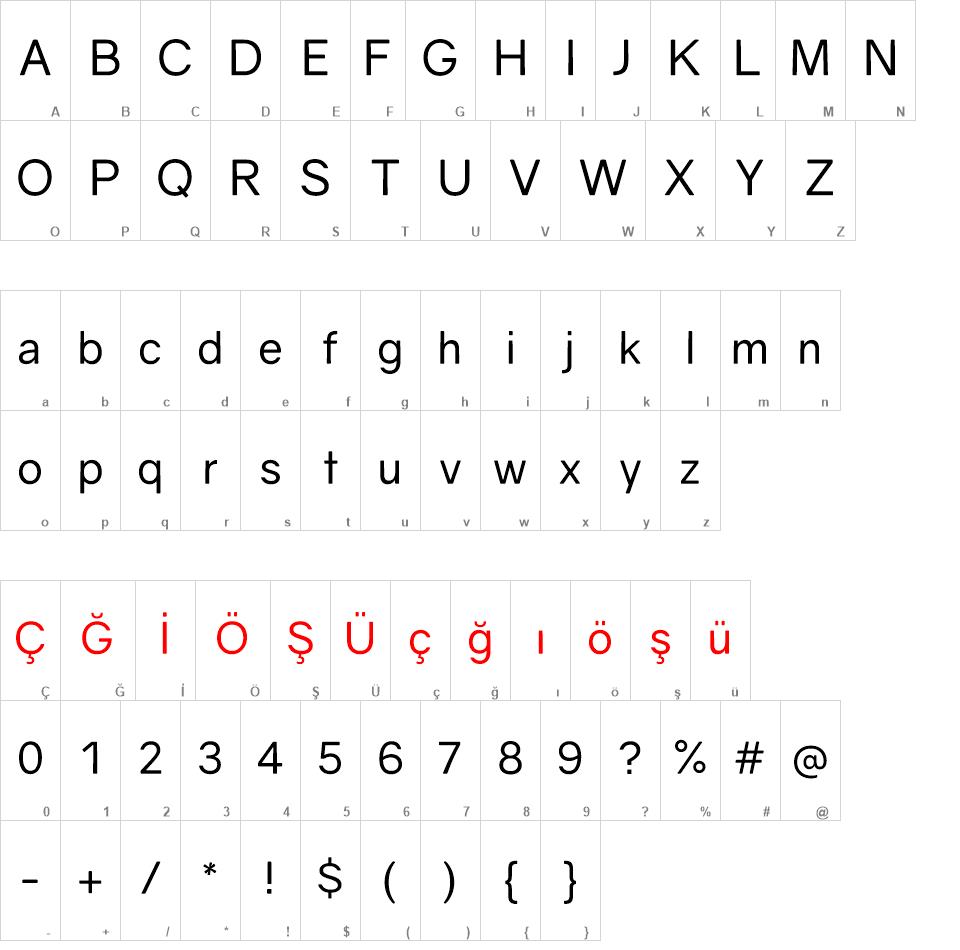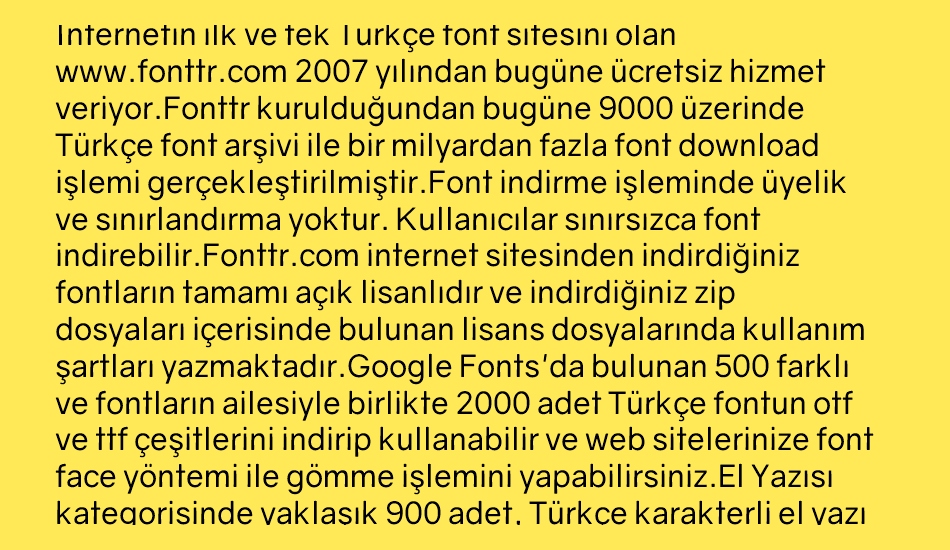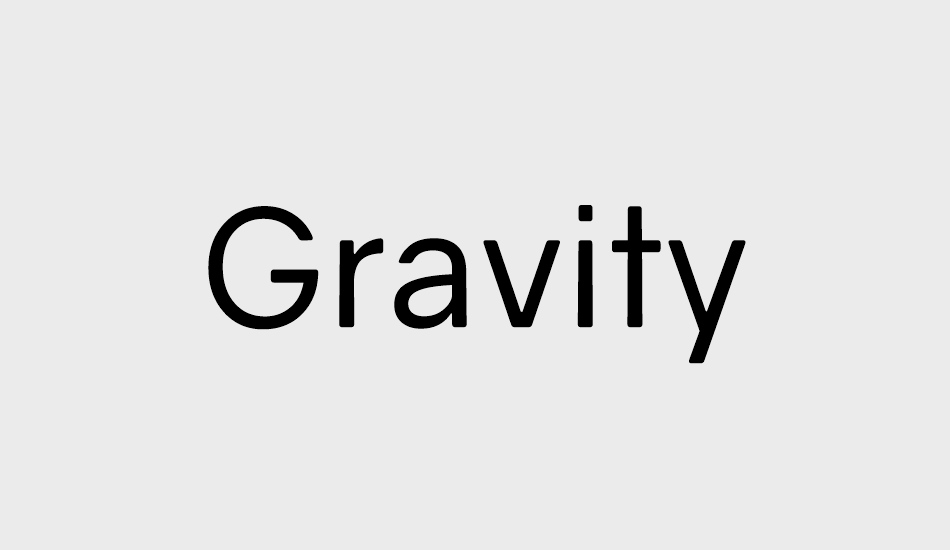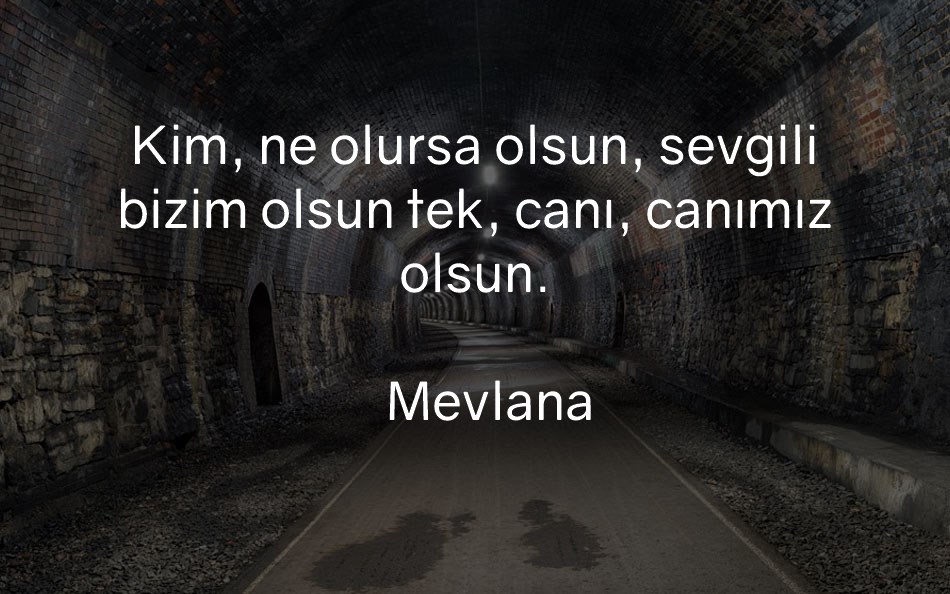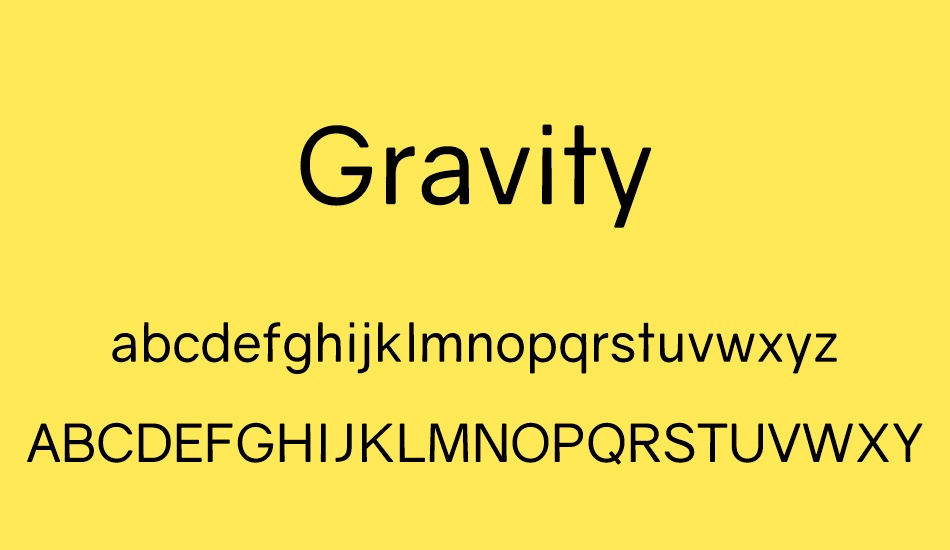
Gravity font
Tasarım dünyasında uzay-yaş tarzı fontlar olmadan ne yapardık? Muhtemelen deliririm. 1997'de, daha önce Chank ve Larabie gibi insanları başkalarının yapmadığı harika yazı tipleri yaptığını fark etmeden önce, "Vahşi Yazı Tipleri" nin Brush Script ve Hobo'dan oluştuğunu düşünen aptal üniversite öğrencisiydim. Gerçek tutmak için dışarı iki upz out bağırmak ve Steve Guttenburg için, diğerleri gibi Polis Akademisi skillz sportin 'için bağırmak.